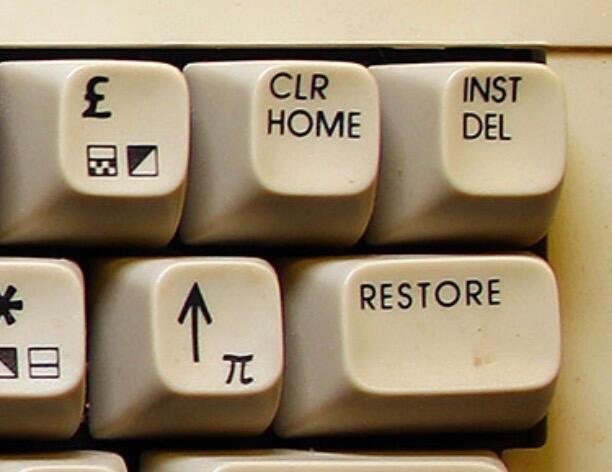
Suche Schrift der Sonderzeichen auf einer Commodore 64C-Tastatur
ich suche verzweifelt die Schrift der Sonderzeichen dieser durchaus weit verbreiteten C64C-Tastatur. Die Schriftart der "normalen" Tasten ist ITC AvantGarde, aber welche Schriftart entstammen die Sonderzeichen "π" (Pi), £ (Pfund) und "Pfeil nach oben"? Kann hier jemand weiterhelfen?
Hallo, danke für deine Antwort. Du hast natürlich recht, es ist möglich, dass Commodore die Zeichen gezeichnet hat und nicht aus einem Font genommen hat. Eben das versuche ich auszuschließen, indem jemand hier vielleicht die Schrift(en) erkennt.
Die verwendete Schrift der "normalen" Tasten ist eben ITC AvantGarde, die aber beim Pfund-Zeichen deutlich abweicht. Das Pi-Zeichen gibt es gleich gar nicht bei ITC AvantGarde und Pfeil nach oben auch nicht.
Dieser Style der Schriften und Sonderzeichen wurde übrigens auch auf dem Commodore 128 und dem nie auf den Markt gebrachten Commodore 65 verwendet.
Bei noch älteren Tastaturen hat sich Commodore etwa beim Font Microgramma bedient, mit dem sie auch die ältere Version ihres Logos gestaltet hatten.